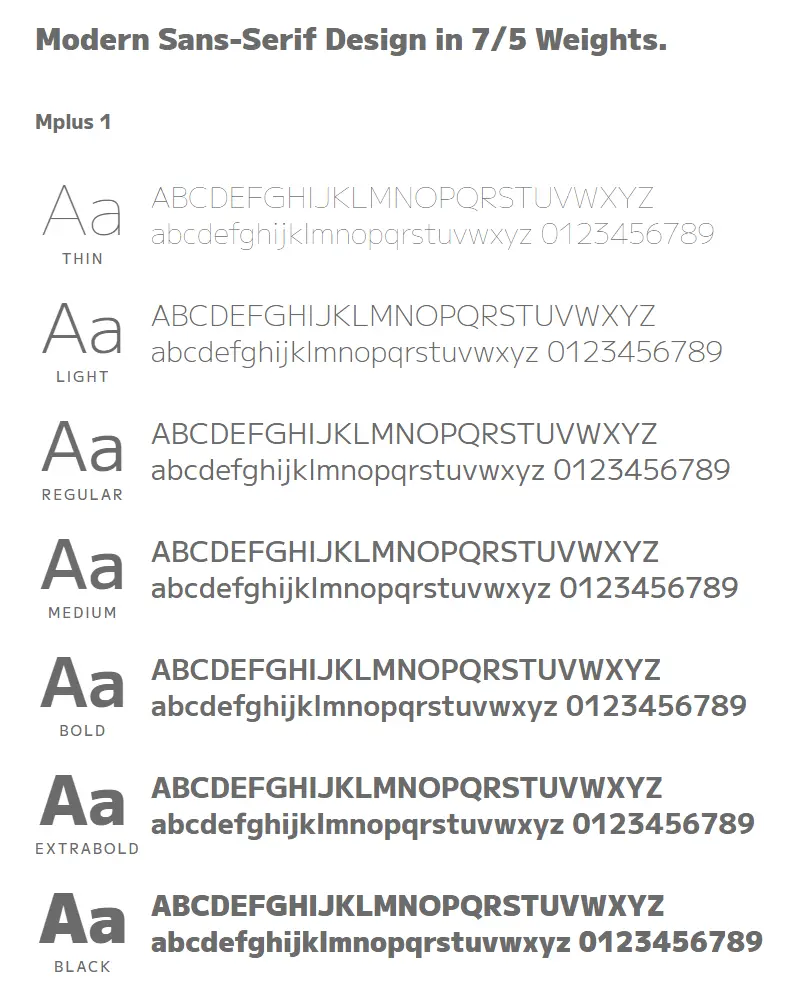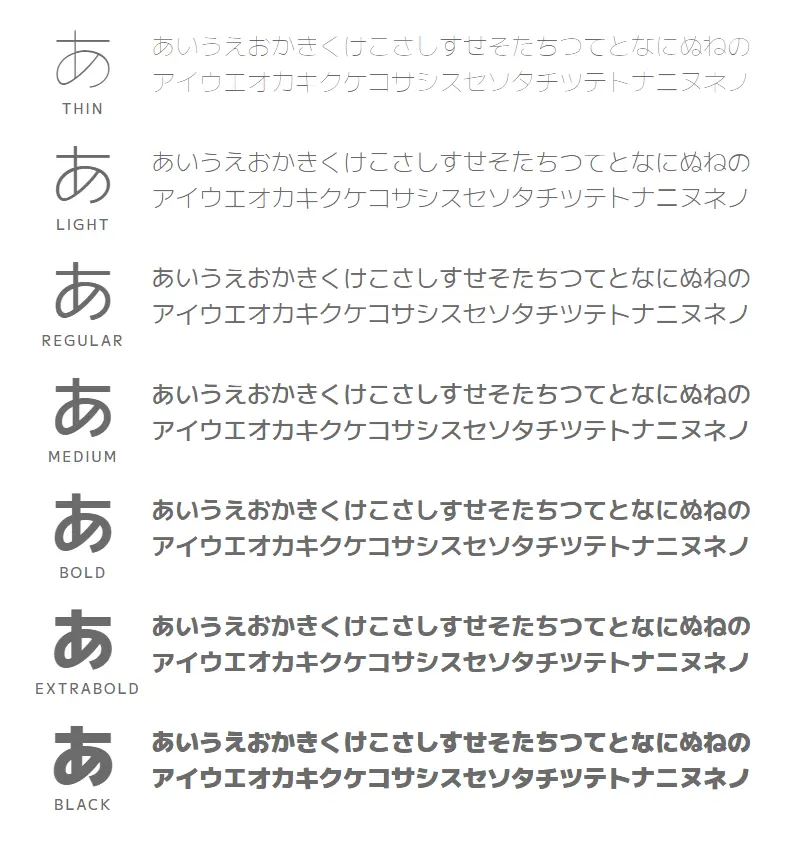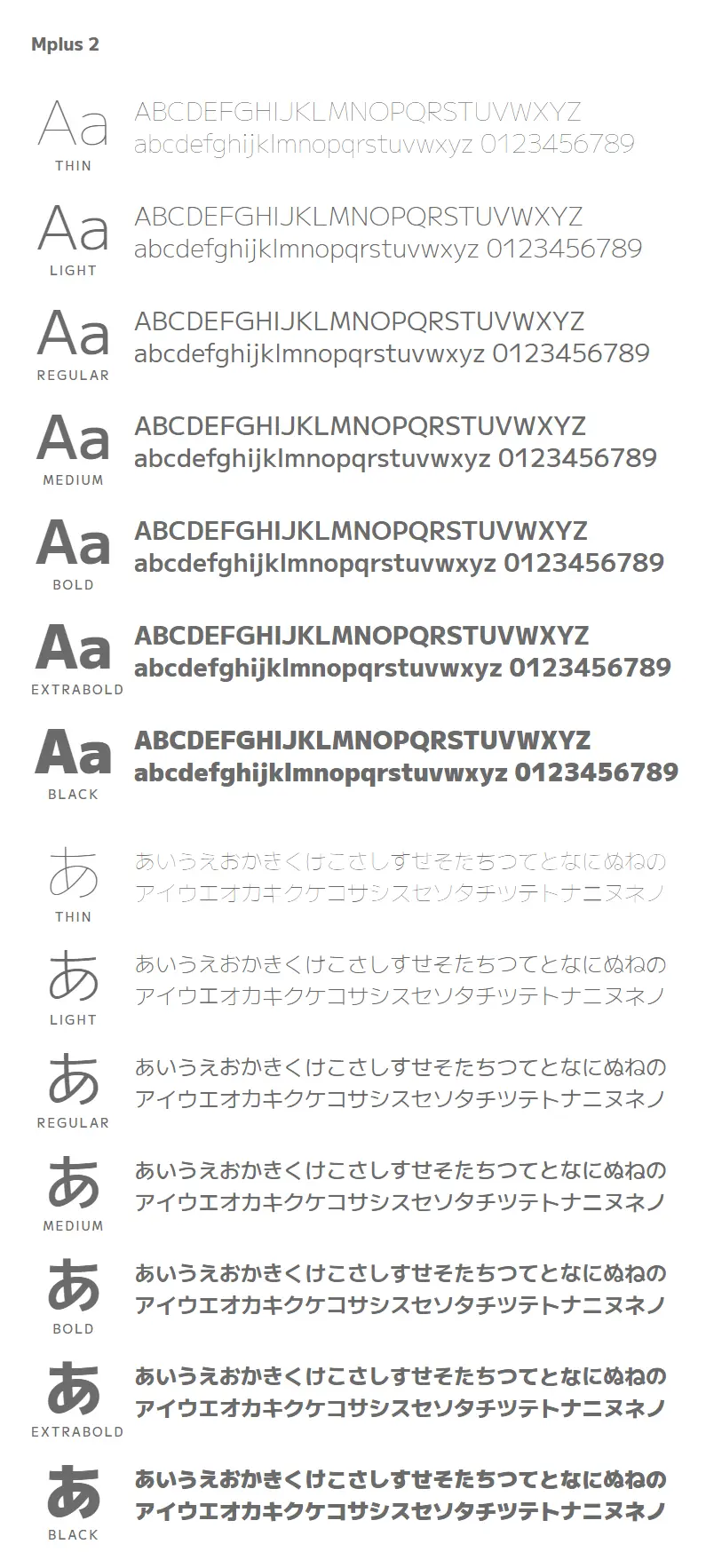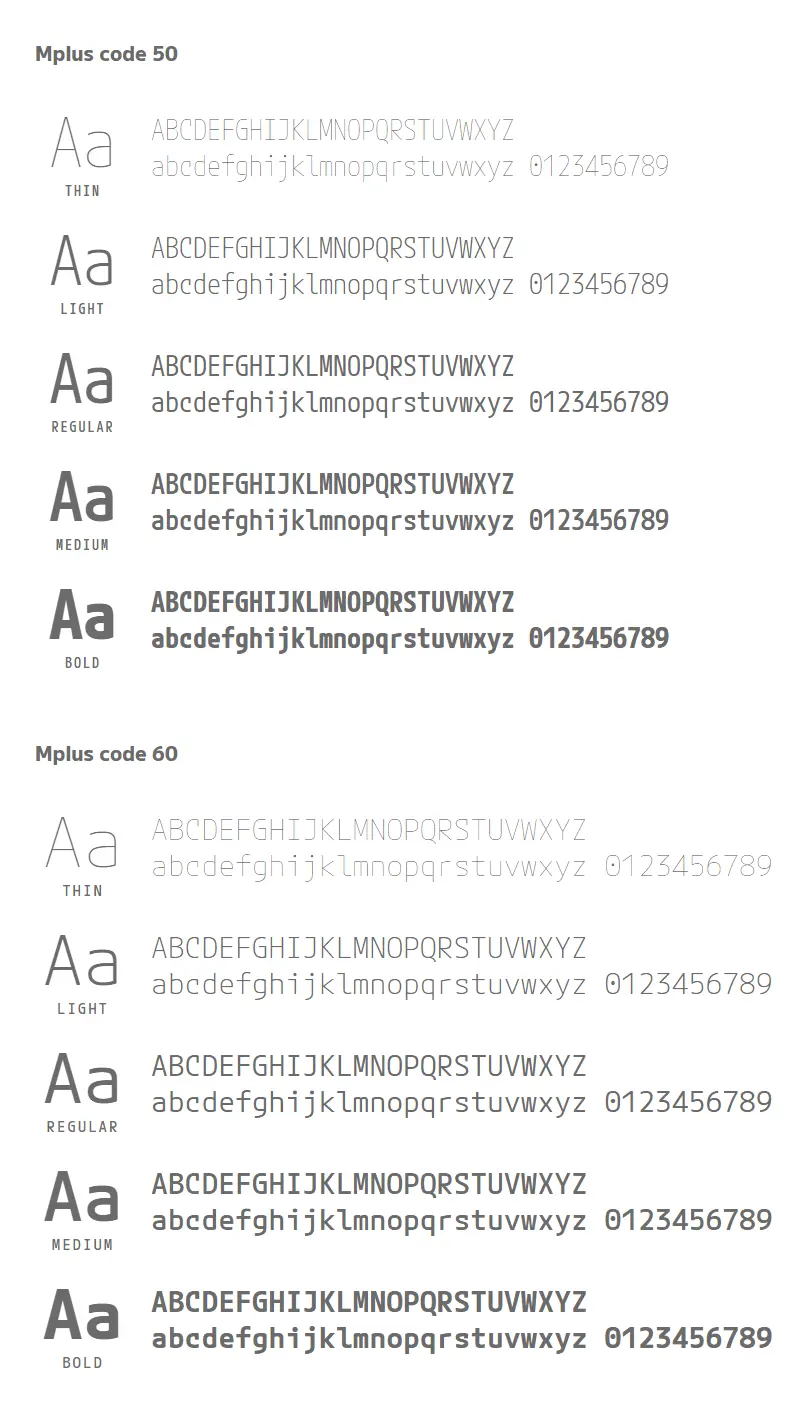
M+FONTS最早發佈於2003年,目前M+FONTS發佈了M+2版本,並新增了可變字形,包括 5700+ 漢字形,並把字體以OFL授權釋出。
M PLUS 1/2 是無襯線字體,從細到黑有 9 個粗細,支持 GF Latin Plus 字形集,日語有 5700+ 個漢字。
Mplus1:舒適的曲線和直線的和諧,這種字體給人以現代而慷慨的印象,適合任何場合,包括小文本到大標題。
ゆったりとした曲線と直線を組み合わせた特徴的なデザインは、小さな本文から大きな見出しまで読みやすく、文章を明るくモダンでやさしい印象にします。
Mplus2:憑藉有些經典的字體形式,這種字體追求經典現代的新標準。
ちょっとだけクラシックな雰囲気を殘したデザインは、モダンになりすぎず、かといって従來的なデザインとも異なる、新たなスタンダード書體を目標としました。
M PLUS Code Latin 50/60:從細到粗的 7 種字重。有 2 種樣式,M PLUS 代碼拉丁語 50 和 M PLUS 代碼拉丁語 60,每種樣式都有 50% 和 60% 的字符寬度。
薄から 粗體 までの 7 つのウェイト。文字幅 50% の M PLUS Code Latin 50 と、文字幅 60% の M PLUS Code Latin 60 の 2 種類があります。